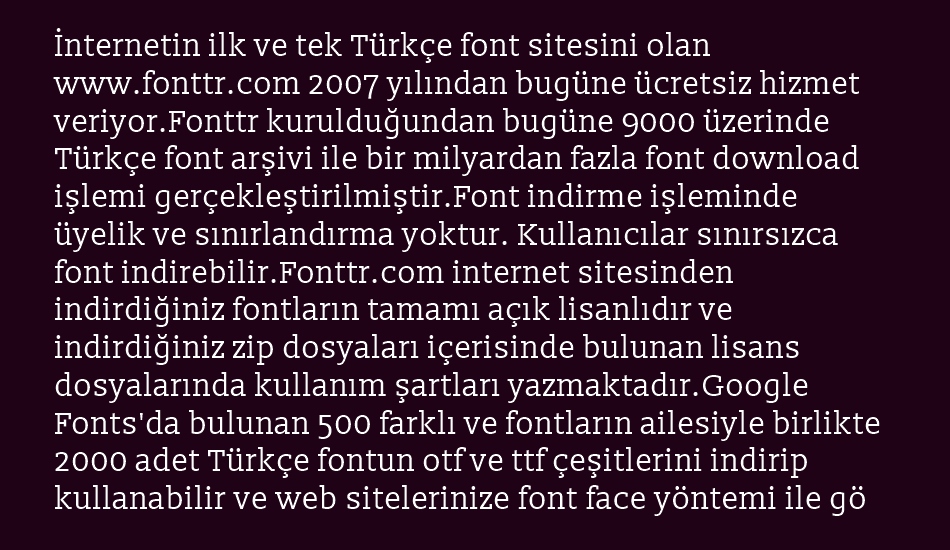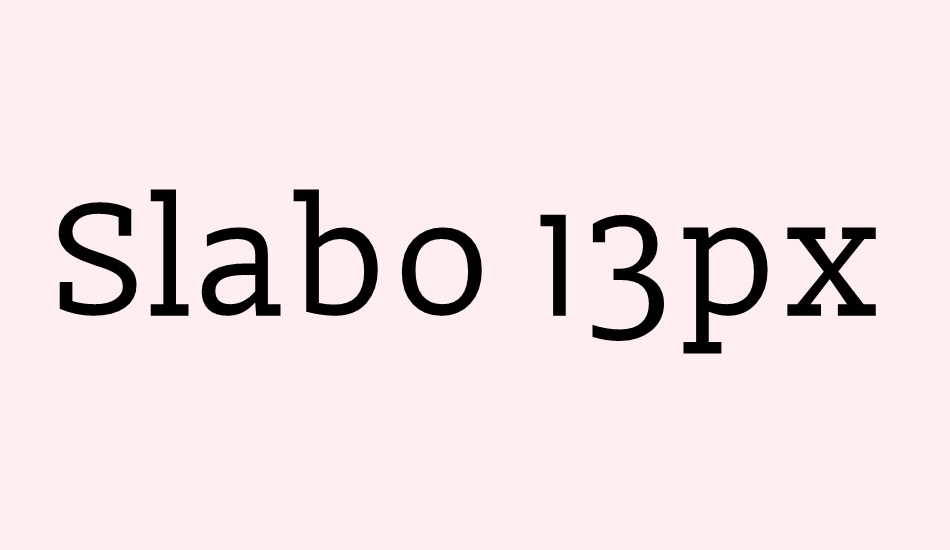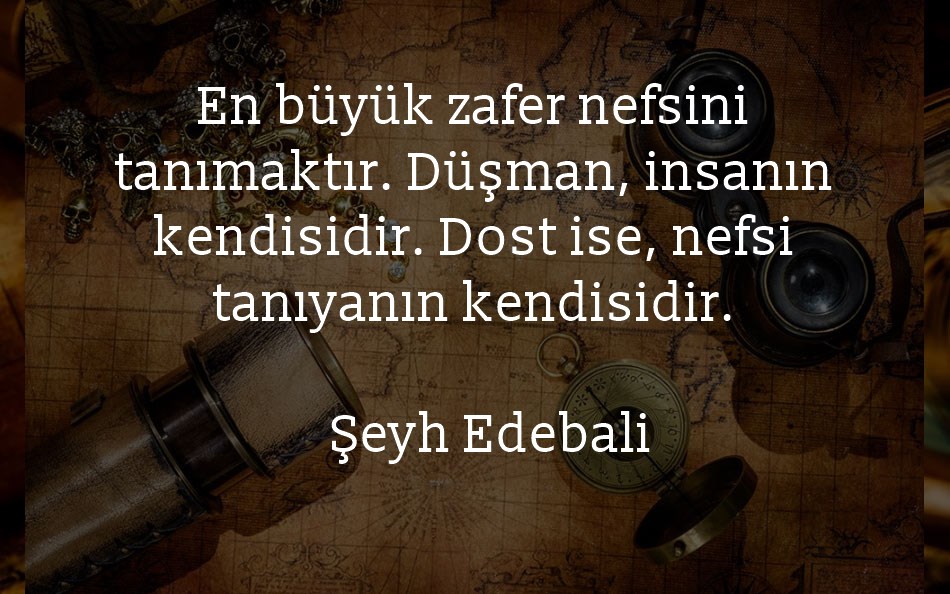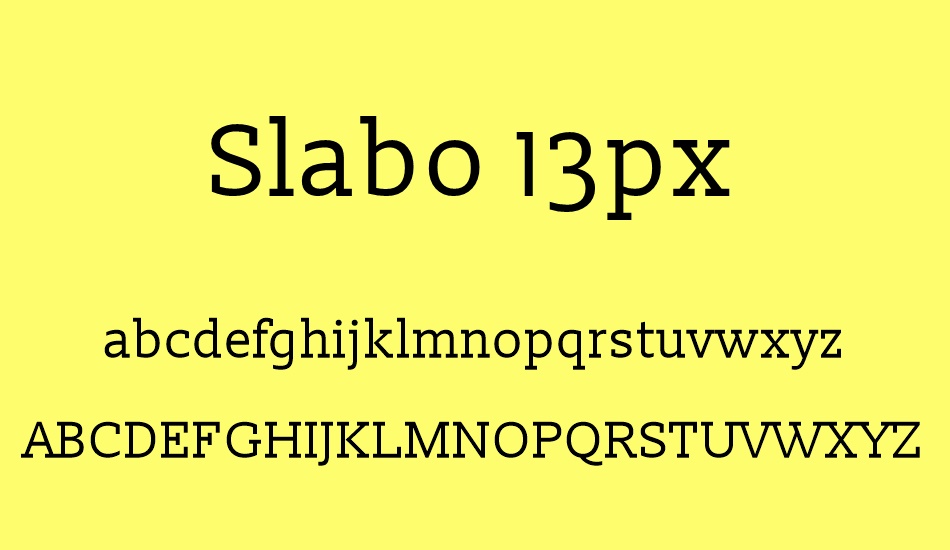
Slabo 13px font
Slabo, çevrimiçi reklamcılıkla ve diğer web kullanımlarında kullanılmak üzere boyuta özel fontların bir toplamıdır. Koleksiyon şu an bu yazı tipi, Slabo 13px ve Slabo 27px içeriyor. Koleksiyondaki her yazı tipi, adının piksel boyutunda kullanılmak üzere ince ayarlanmıştır.
Slabo font projesi, Kanada merkezli tip tasarım dökümhanesi Tiro Typeworks tarafından yönetiliyor.